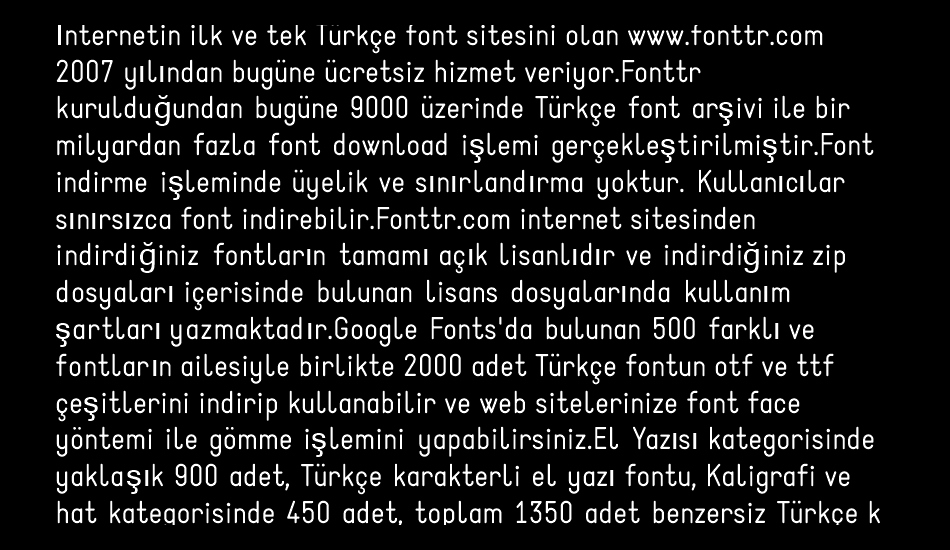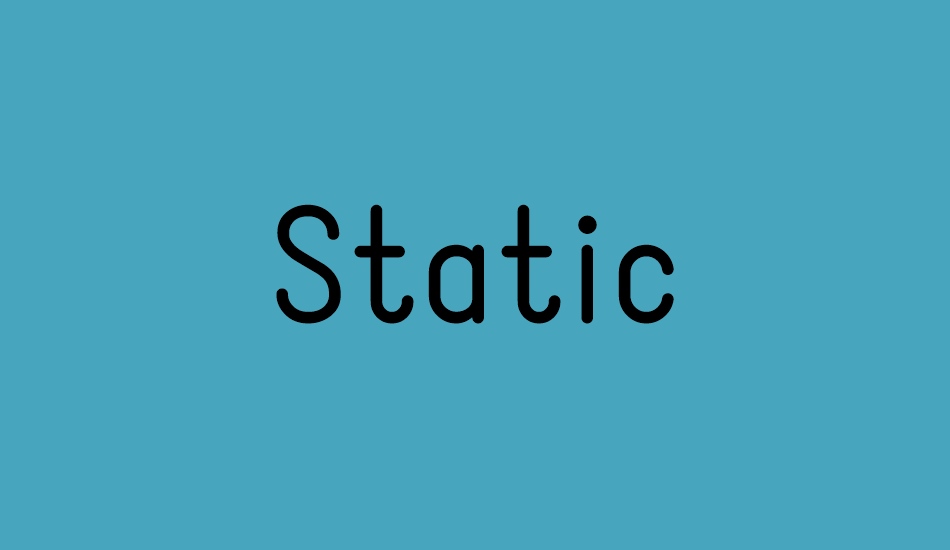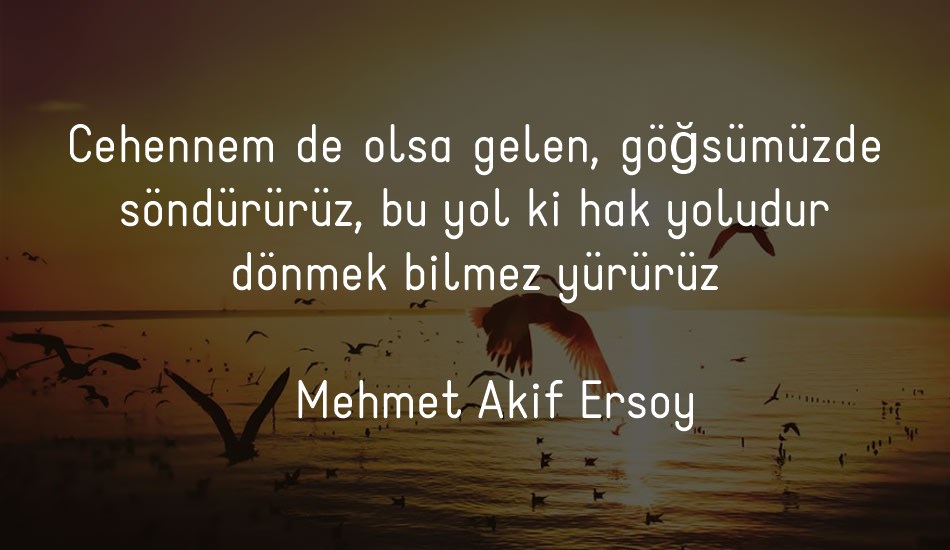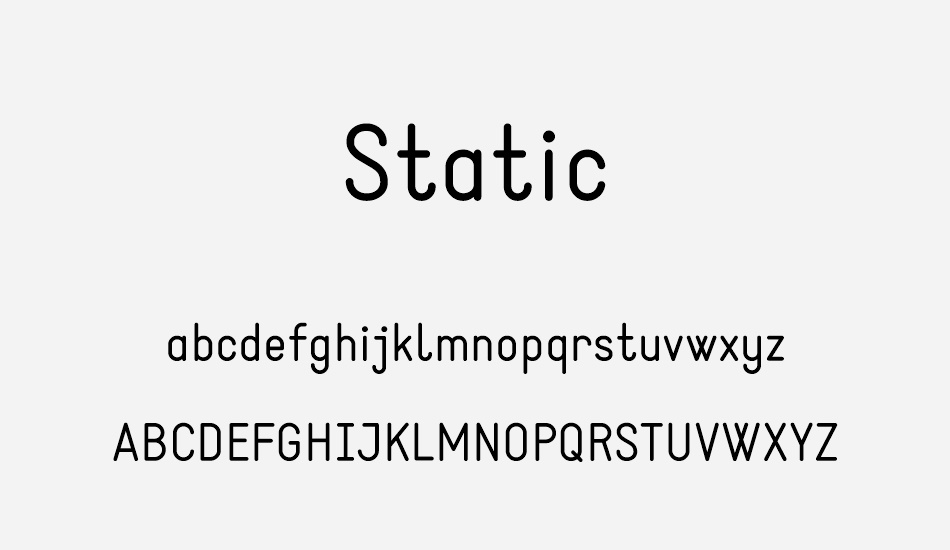
Static font
Static, monospaced tarzda güçlü geometrik formlarla oluşturulmuş çağdaş bir özgür yazı tipi. Her türlü grafik tasarımı için uygundur - web, baskı, hareketli grafik vb. Ve tişörtler ve posterler, logolar gibi diğer öğeler için mükemmeldir.